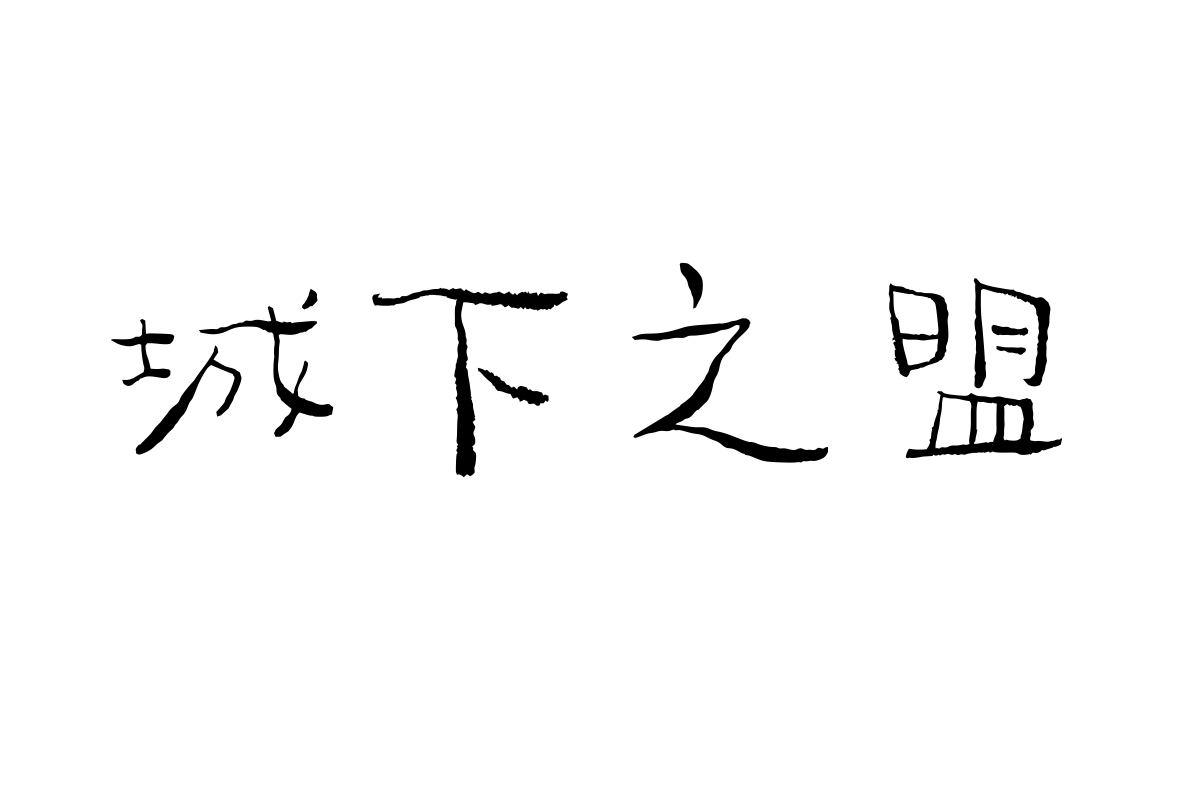
汉仪俊坡隶字体是**一款具有浓厚古拙意味的隶书作品,由汉仪字库官方出品。该字体以汉代《张迁碑》和《石门颂》结体为基础,形成书风端正朴茂、结体巧妙大方的特点**。
汉仪俊坡隶字体适合应用于艺术设计、平面宣传设计、海报设计、书法字帖等领域。其笔触轻且细,融合了隶书的特点,使得字体既有艺术效果,又易于应用在各种设计作品中。
总的来说,汉仪俊坡隶字体是一款非常适合艺术创作和设计领域的字体,无论是用于平面设计还是书法创作,都能展现出独特的魅力和效果。